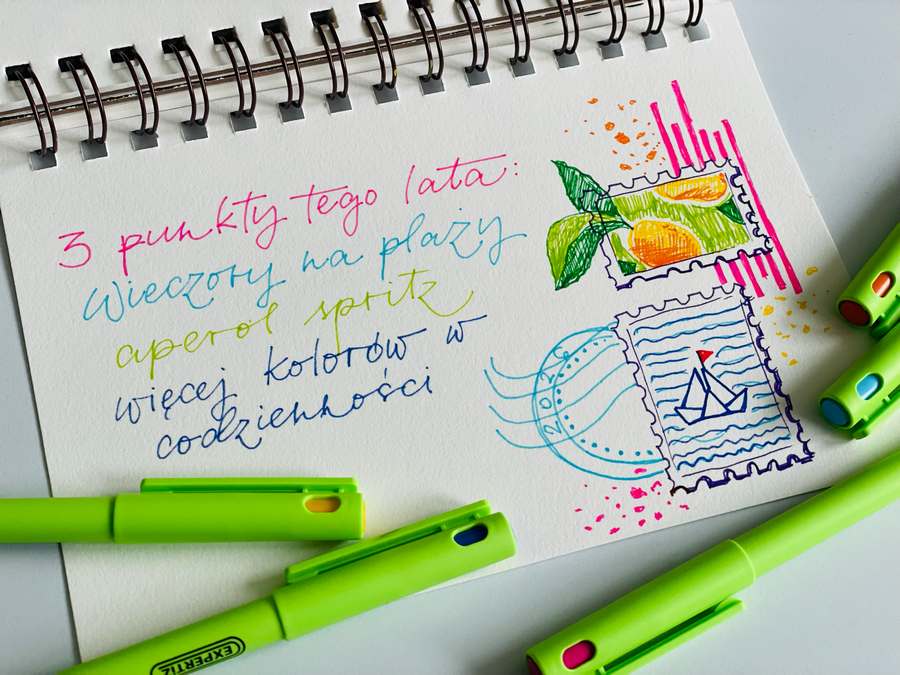
Moje serce mocniej bije na widok pięknych kolorowych liter. Fascynują mnie piękne kolory- czy to w literach, czy w ilustracjach- nie mogę oderwać od nich wzroku. Dlatego tak chętnie tworzę nowe plakaty letteringowe oraz proste ilustracje, które cieszą oko. Chętnie dzielę się z innymi moją pasją.
Rozpocznij już dziś swoją przygodę z hand letteringiem
W dobie rozwiniętych technologii permanentnym korzystaniu ze smartfona, laptopa, czy tableta, pisanie ręczne stało się rzadką czynnością. Wysyłanie kartek okolicznościowych jest coraz mniej popularne- szybki sms, mail, WhatsApp załatwia sprawę. Umiejętność pisania i malowania ozdobnych liter jest raczej rzadkością. Pragniesz rozpocząć swoją przygodę z pięknymi literami? Czekają tutaj na Ciebie kursy online, szablony do druku oraz mnóstwo inspiracji na blogu.